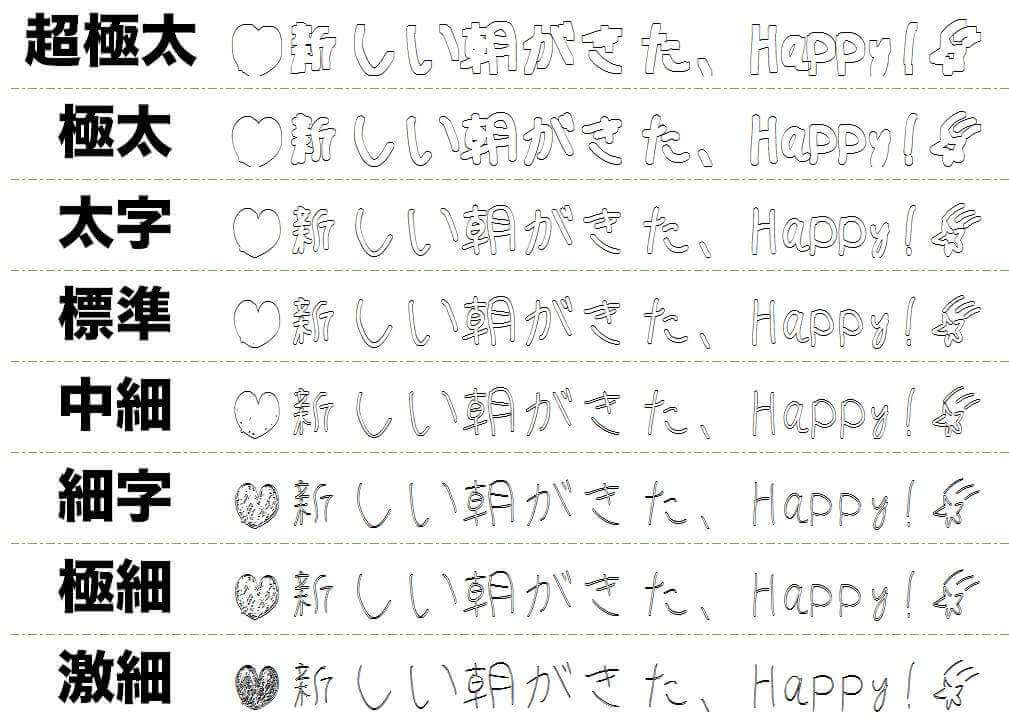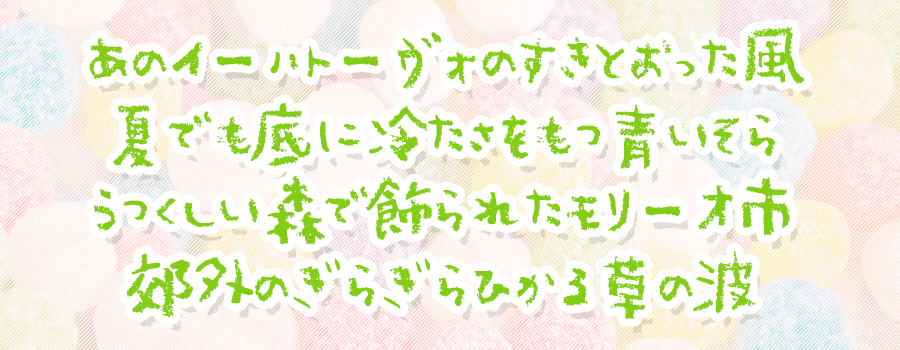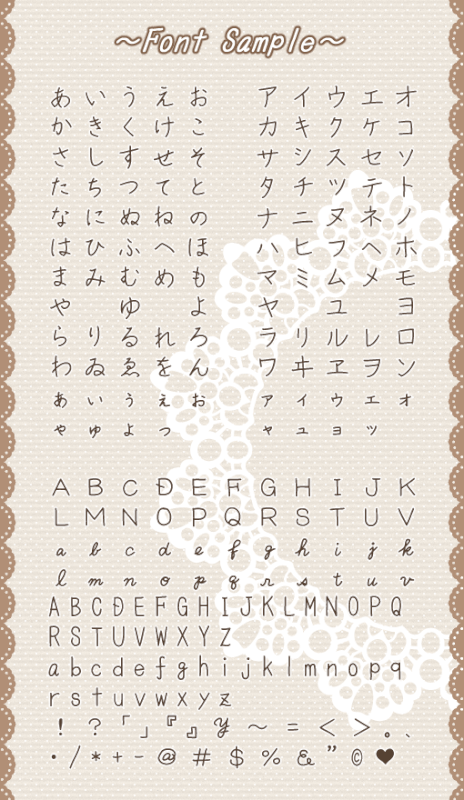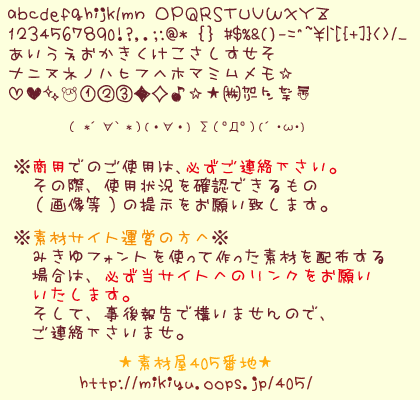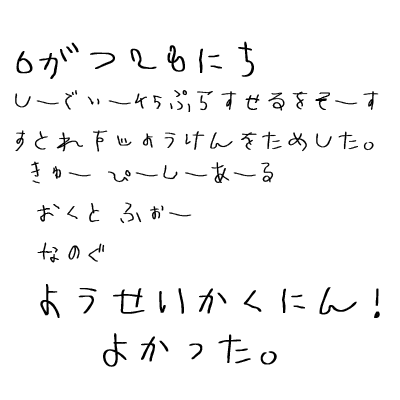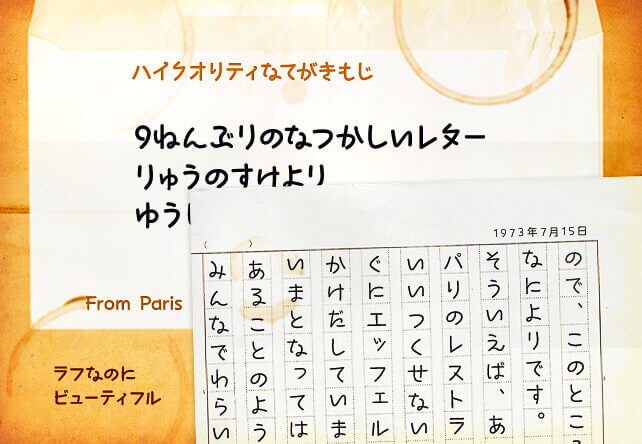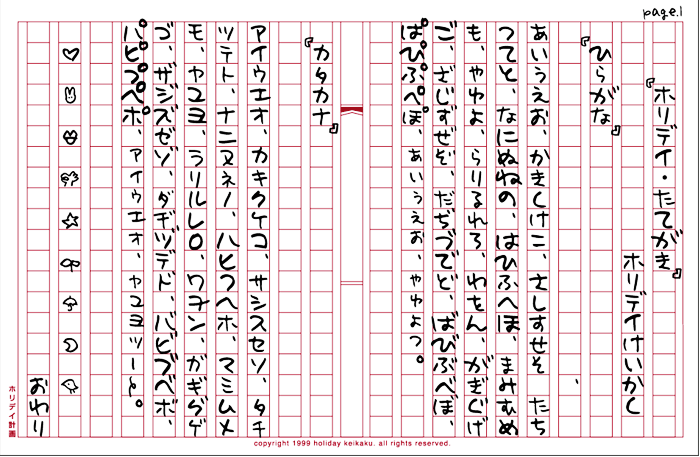
無料で使えるフリーハンドで書いたへた字フォント23個
無料でダウンロードできるフリーハンドフォントを集めました。「手書きフォント」の記事と比べて、より崩して書いた書体をこちらにまとめています。中にはわざとへた字を再現したリアルな直筆に近いフォントもございます。あたたかみのあるチラシやポップのデザインを作成する方は当ページをご参考ください。
IKれんめんちっく
タテに組むと連綿体のように文字がつながる、タテ組み専用2バイトひらがなフォント。連綿体とは行書や草書の文字を続けて書く書体。タテ組みとベタ組み(カーニング/トラッキング値が0)の設定が可能なソフトが必要。
miu font
フォント製作者の愛猫ミウをイメージして作られたフォント。猫のしっぽみたいなイメージ。
rehabilitation – リハビリフォント
病気と戦う患者さんがリハビリで書いた文字を、許可を得てフォント化したもの。
S2Gうみフォント
手書き文字から作成されたフォント。手紙などに使用するとかわいらしい印象を与える。
Sampomichi HR
デコボコした文字組みと、直線と曲線によるデザインによって描き出された遊び系1byteひらがなフォント。かわいい雰囲気を出したいロゴ文字にピッタリ。
Tokage-no-Shippo HR
アラビア文字のような独特のウネリと、大胆な筆跡を併せ持った、癖の強い手書き風ゴシック体の、1byteひらがなフォント。
ちまころん
ちまちまころころとした(?)手書きフォント。収録文字は、アルファベット・記号・ひらがな・カタカナなど。
ふい字
縦書きに対応している日本語かな文字フォント。「ふい字」は等幅、「ふい字P」はプロポーショナル。
ホリデイ たてがき-KT, HR
ひらがなとカタカナの縦書きフォント。縦書きのHP制作に最適。
まじぱねぇ
ギャル文字風の手書きフォント。文字が「ね」→「Ne」、「し」→「U」、「ん」→「ω」のように入れ替わる。手紙やプリクラ風の写真などを作るのに向いている。
みきゆフォント -Honey Candy-
2バイトフォント。アルファベット、ひらがな、カタカナ、数字と、一部の記号のみ。
みきゆフォント NEWペン字P
漢字が使えるフォント。漢字は、JIS第一水準・第二水準が全て使用可能。第三水準も一部収録。
みきゆフォント ペン字P
漢字が使えるプロポーショナルフォント。漢字は、JIS第一水準・第二水準が全て使用可能。第三水準も一部収録。
みきゆフォント(みきゆフォント 1st)
2バイトフォント。アルファベット、ひらがな、カタカナ、数字と、一部の記号のみ。
ようじょふぉんと
文字を覚えたての就学前の子ども(3~5歳ごろ)をイメージして作られた日本語フォント。 収録されている文字はひらがな・数字とごく一部の記号のみ。
りゅうのすけフォント
男性のラフな手書き文字を参考にして作られた書体。文字で「ラフな勢い、懐かしいやさしさ」を表現したい時に威力を発揮するフォント。
れぃぞう
手書きの2バイト等幅フォント(文字幅が全て同じもの)。ちょっと角がとんがってる感じの文字。